2023 年ベスト シャドウ フォント 27 (無料およびプレミアム)
公開: 2023-08-03あなたはプロジェクトを次のレベルに引き上げたいと考えているグラフィック デザイナーですか? 創造性と洗練さをさらに加える完璧なフォントをお探しですか? これ以上探さない!
このブログ投稿では、あなたのデザインゲームを向上させる 27 個の最高のシャドウ フォントを紹介します。
さて、シャドウ フォントとは一体何なのか、疑問に思われるかもしれません。 シャドウ フォントは、文字の後ろに影があるように見え、立体感を生み出すタイポグラフィの一種です。
あらゆるデザインに深みと立体感を加えるため、デザイナーの間で人気の選択肢です。 実際、調査によると、シャドウ フォントを使用すると、デザインの読みやすさと記憶しやすさが最大 40% 向上することがわかっています。
この記事では、市場で入手可能な最高のシャドウ フォント 27 個を紹介します。 各フォントは、そのユニークなスタイル、多用途性、品質を考慮して慎重に厳選されています。
ロゴ、Web サイトのデザイン、印刷プロジェクトのいずれに取り組んでいる場合でも、これらのフォントは、視覚的に魅力的で魅力的なデザインを作成するのに役立ちます。 それでは、シャドウ フォントの素晴らしい世界に飛び込んで発見してみましょう!
最高のプレミアムシャドウフォント
あなたのデザインプロジェクトにさらに深みと立体感を加えてみませんか? 最高のプレミアム シャドウ フォントの厳選されたコレクション以外に探す必要はありません。
これらの革新的で視覚的に印象的な書体は、あなたのデザインを新たな高みに引き上げることが保証されています。そのため、詳しく見て創造的な可能性の領域を解き放ってみてはいかがでしょうか。
モッドスター
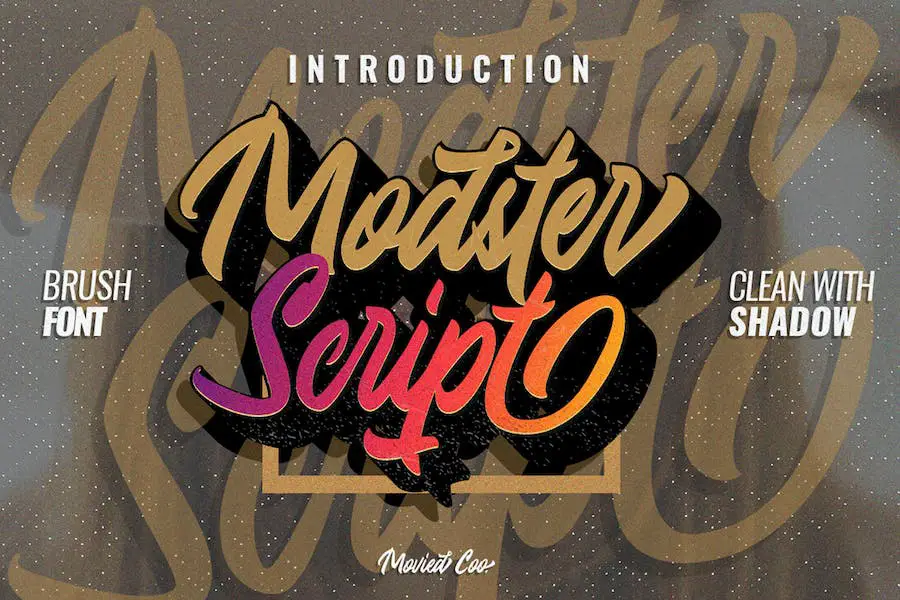
Modster は、プロジェクトのデザインを向上させたいグラフィック デザイナーにとって素晴らしいフォントです。 このシャドウ フォントは、愛情を込めたハンドレタリングからインスピレーションを得た、ユニークで都会的なスタイルを提供します。
さらに、Modster にはさまざまな代替手段が用意されており、デザイナーが実験して独自の個性を加えることができます。 これらの代替案には各文字のオプションが用意されており、デザイナーはこのフォントをカスタマイズして真にユニークなデザインを作成できます。
Modster の際立った機能の 1 つは、追加のシャドウ効果が含まれていることです。 これによりテキストに深みと立体感が加わり、視覚的に魅力的で目を引くものになります。 影を使用すると、全体のデザインが強化され、競合他社よりも目立つようになります。
ブラックロマンス
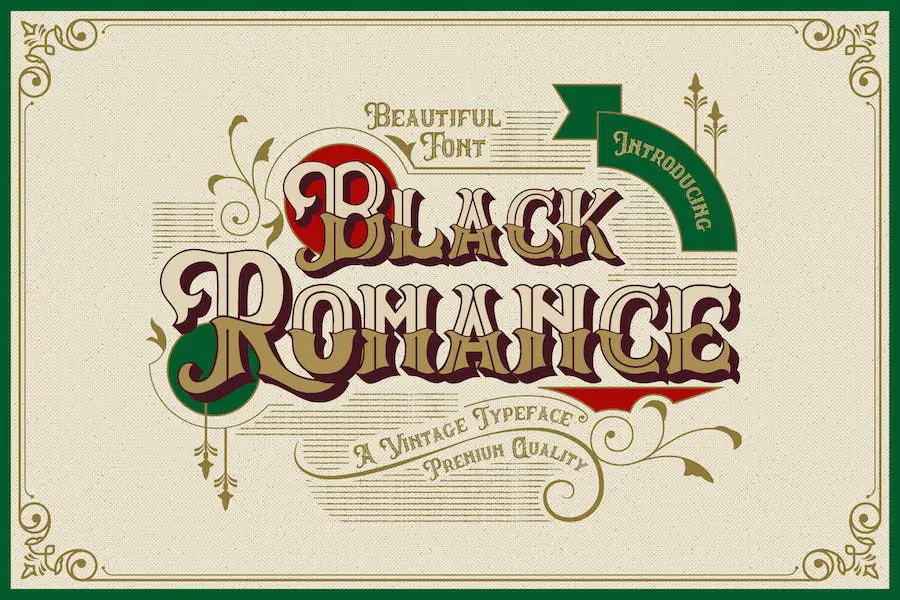
Black Romance は、あらゆるデザイン プロジェクトに優雅さとビンテージ感をもたらす素晴らしいフォントです。 ブラックレターの美しさを備えたこのフォントは、デザインに大胆で装飾的な要素を追加するのに最適です。
このフォントは非常に多用途で、幅広い目的に使用できます。 製品ラベル、ブランディング素材、招待状、バナー、映画タイトルなど、あらゆるものを作成する場合、Black Romance はあなたの作品に魅惑的な魅力を加えます。
ヴィンテージの雰囲気とブラックレターの美学を備えた Black Romance は、デザイン プロジェクトに魅力と洗練さを加えたいと考えている人にとって最適なフォントです。 今すぐダウンロードして、あなたの創造力を羽ばたかせてください。
エルカトラズシャドウ
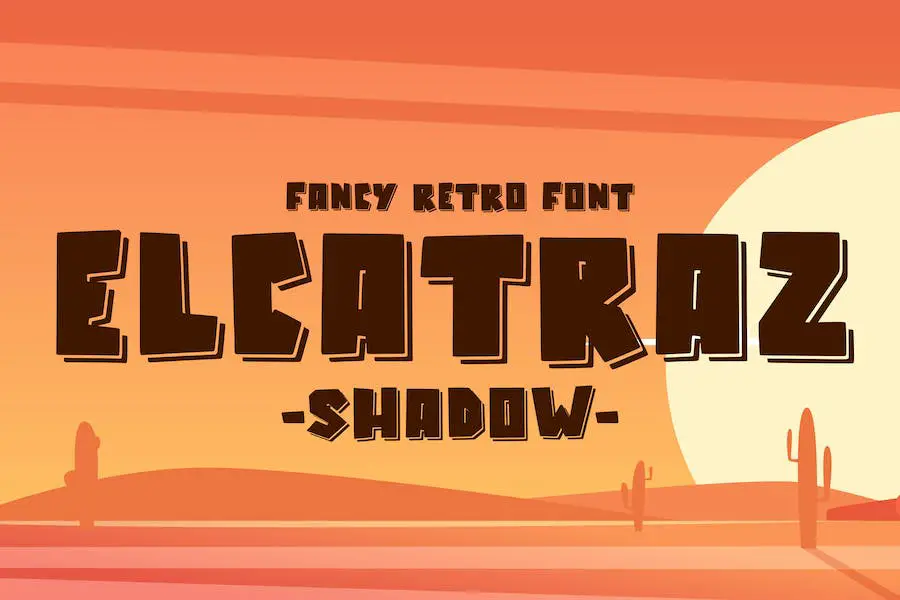
Elcatraz Shadow は、さまざまなクリエイティブ プロジェクトのデザインを強化する多用途フォントです。
工芸品、製品パッケージ、ラベル、ブランディング、ロゴ、ビンテージのソーシャル メディア投稿、広告、透かし、招待状、文具、またはその他のプロジェクトに取り組んでいる場合でも、このフォントは完璧な選択です。
Elcatraz Shadow は、そのユニークなシャドウ効果により、デザインに深みと視覚的な面白みを加え、プロフェッショナルで目を引く外観を与えます。 このフォントをあなたの作品に組み込むと、作品が際立ち、見る人に永続的な印象を残すことになるでしょう。
バーフォード
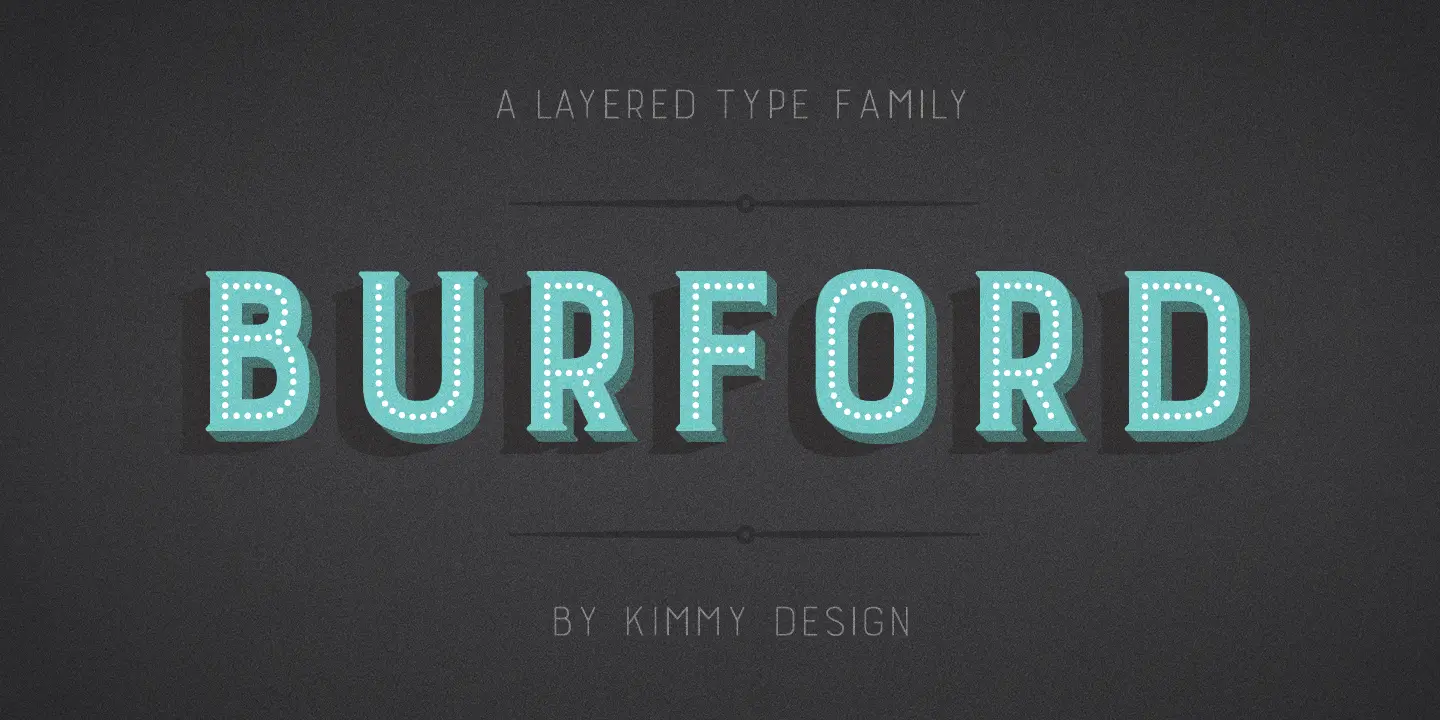
Burford は、Kimmy Design によって作成された注目のシャドウ フォントです。 あらゆるデザインプロジェクトにクールでスタイリッシュなタッチを加え、自分の作品を向上させたいグラフィックデザイナーに最適です。 このフォントには、他のフォントから目立つようにするさまざまな属性が備わっています。
Burford は、その見事なビジュアルに加えて、優れた可読性と可読性も誇っています。 つまり、影の効果があってもテキストは鮮明で読みやすく、メッセージが効果的に伝わります。
したがって、プロジェクトを次のレベルに引き上げるクールなシャドウ フォントを探している場合は、Kimmy Design の Burford 以外に探す必要はありません。 この注目に値するフォントを使用して、デザインにスタイリッシュでプロフェッショナルな雰囲気を与えましょう。
ママキッズ
Moms Kids は、グラフィック デザインの世界における母親と子供のニーズを満たすために設計された、特別なフォントの楽しいセットです。
これらのシャドウ フォントはプロジェクトに独特のタッチを提供し、デザイナーがデザインを向上させ、閲覧者にとって視覚的に魅力的なエクスペリエンスを作成できるようにします。
目立たせるためのさまざまな属性を備えた Moms Kids フォントは、デザインに魅力的で遊び心のある要素を追加したい人にとって必須のフォントです。
あなたのデザインに愛と奇抜なタッチを加えるシャドウ フォントをお探しなら、Moms Kids 以外に探す必要はありません。 これらの特別なフォントは、親愛なる母親と子供たちを念頭に置いてデザインされており、幅広いスタイル、多用途性、細部へのこだわりを備えています。
スーパーリトル
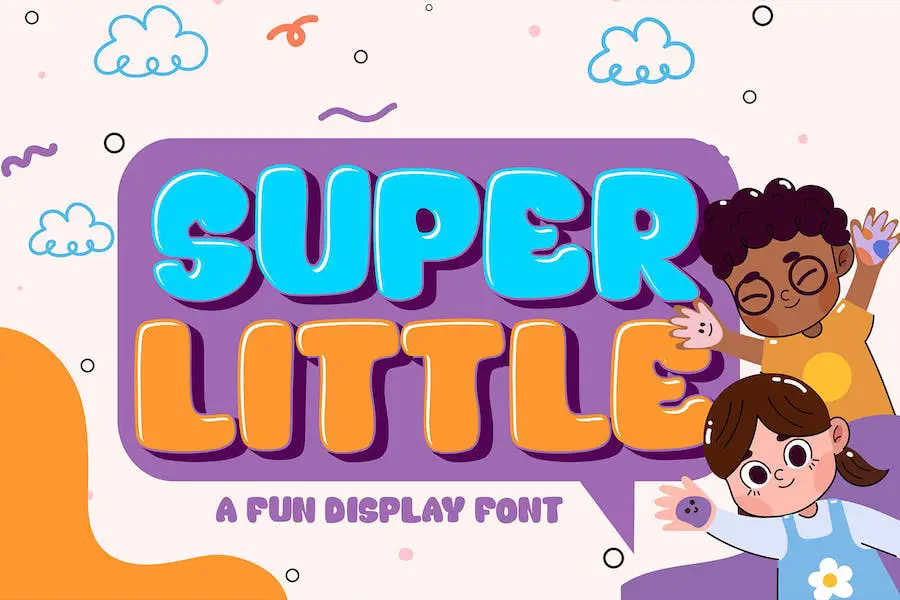
Super Little は、デザイン プロジェクトに影の装飾を加える、楽しくてスタイリッシュな表示フォントです。 ブランディング、見出し、結婚式のデザイン、招待状、またはその他のクリエイティブな取り組みに取り組んでいる場合でも、このフォントはあなたの仕事を次のレベルに引き上げます。
ユニークで人目を引くデザインの Super Little は、ロゴタイプ、ウォールアートのイラスト、ラベルなどの作成に最適です。 この多用途かつダイナミックなフォントでプロジェクトを強化しましょう。
Super Little の優れた点の 1 つは、さまざまなデザイン スタイルに適応できることです。 モダンで洗練された外観を求めている場合でも、ヴィンテージでレトロな雰囲気を求めている場合でも、このフォントはあなたをカバーします。
ビーチデイ
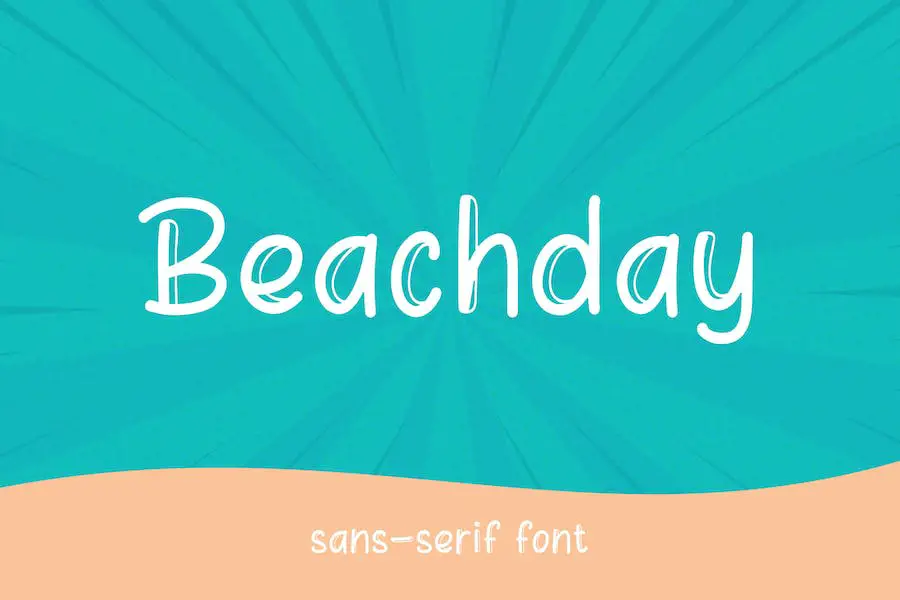
Beachday は、デザインにモダンでクリーンなタッチを加える素晴らしいシャドウ フォントです。 このサンセリフ表示フォントには、すべての単語にハッピーで陽気な雰囲気をもたらす独特の魅力があります。
Beachday の際立った特性の 1 つは、注目を集め、ポジティブな感情を呼び起こす能力です。 フォントのきれいなラインと遊び心のある影の効果が、テキストに喜びと活気をもたらします。
Beachday のもう 1 つの注目すべき特徴は、その読みやすさです。 ユニークでクリエイティブなデザインにもかかわらず、フォントは読みやすく、メッセージが効果的に伝わります。
シャドウビーマー
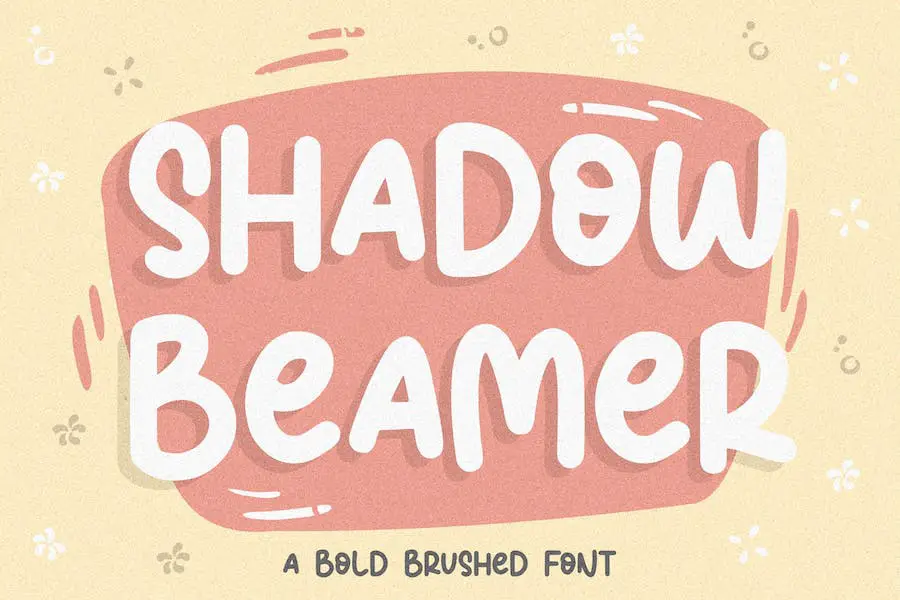
Shadow Beamer は、さまざまなデザイン プロジェクトに最適な、大胆なブラシ フォントです。 製品パッケージの作成、ブランディング プロジェクトの作業、雑誌のレイアウトのデザイン、さらにはソーシャル メディアの投稿のパーソナライズなど、このフォントは優雅さとスタイルのタッチを加えます。
独特のブラシ ストロークが独特の影効果を生み出し、どんな背景に対してもテキストを美しく際立たせます。 Shadow Beamer を使用すると、視覚的に魅力的な方法でメッセージを簡単に表現できます。
素晴らしいシャドウ フォントでプロジェクトを強化したいと考えているグラフィック デザイナーにとっては必需品です。 したがって、Cricut プロジェクトに取り組んでいる場合、Figma でデザインしている場合、または単にデザイン全体を向上させるフォントを探している場合、Shadow Beamer は最適な選択です。
げしな
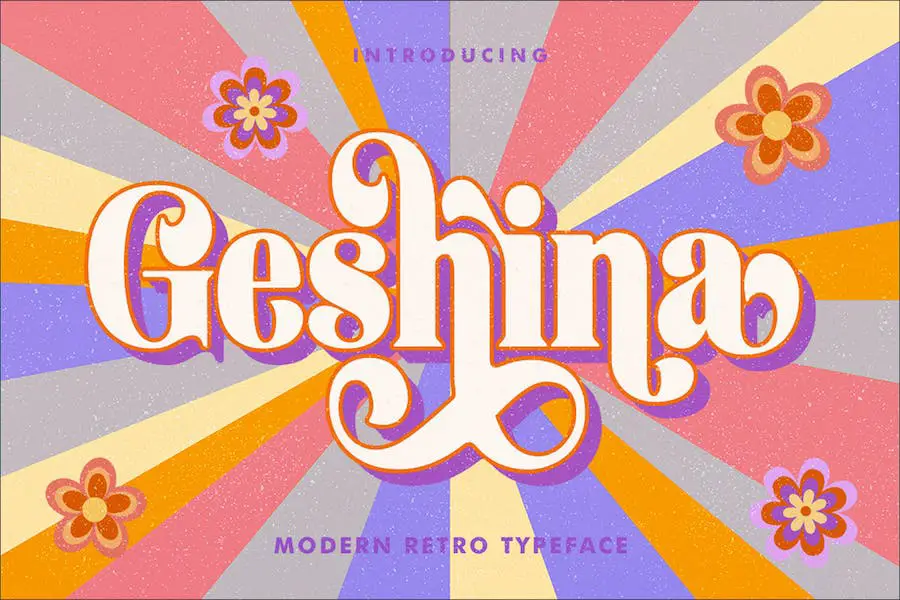
Gesina は、デザインに優雅さを加えるレトロなセリフ フォントです。 曲線的で洗練された文字は、結婚式の招待状、カード、その他ロマンチックで個性的なタッチが必要なデザインの作成に最適です。
Gesina の重要な特性の 1 つは、その多用途性です。 ヴィンテージ風のデザインからモダンでミニマリストなレイアウトまで、このフォントはさまざまなスタイルやテーマにシームレスに適応します。 そのレトロな魅力は、懐かしさを感じさせながらも、新鮮で現代的な感覚を与えます。
Gesina のもう 1 つの大きな特徴は、読みやすさです。 曲線的な文字は目に優しく、本文や長い文章に最適です。 フォントは小さいサイズでも可読性を維持し、メッセージが明確でアクセスしやすいことを保証します。
黒い影
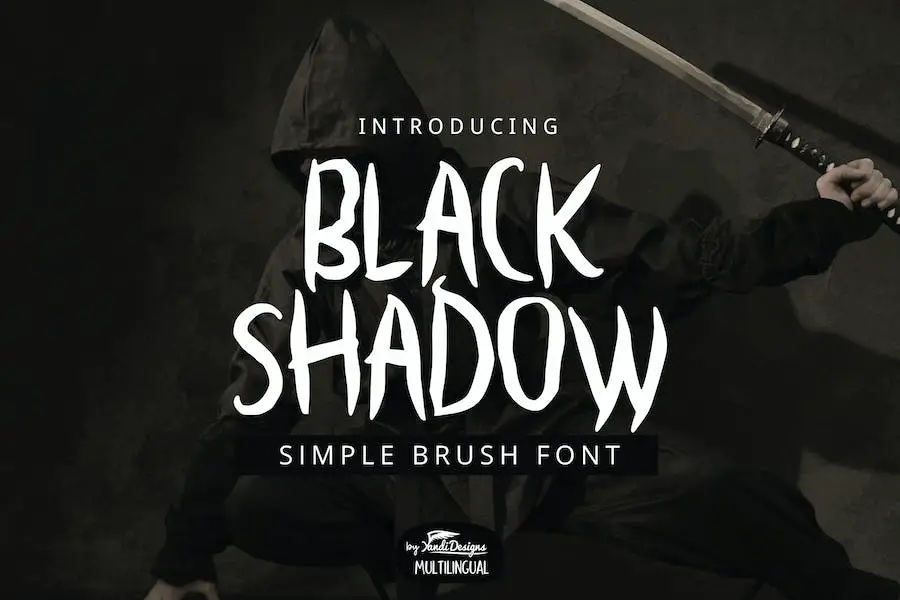
Black Shadow は、あらゆるプロジェクトにシンプルさとユニークさを加える、多用途の手作りブラシ フォントです。 多目的なデザインなので、児童書、引用、ロゴ、見出し、タイトルなどに最適です。
Black Shadow が他のフォントと異なる点は、感情を呼び起こし、雰囲気を作り出す能力です。 手作りのブラシ ストロークはユニークで個人的なタッチを与え、温かみのある心地よい雰囲気を必要とするプロジェクトに最適です。
タトゥー業界にいるなら、Black Shadow は見逃してはいけないフォントです。 その大胆で芸術的なスタイルは、見事なタトゥーのデザインを作成するのに最適です。
ダークサイドシャドウ
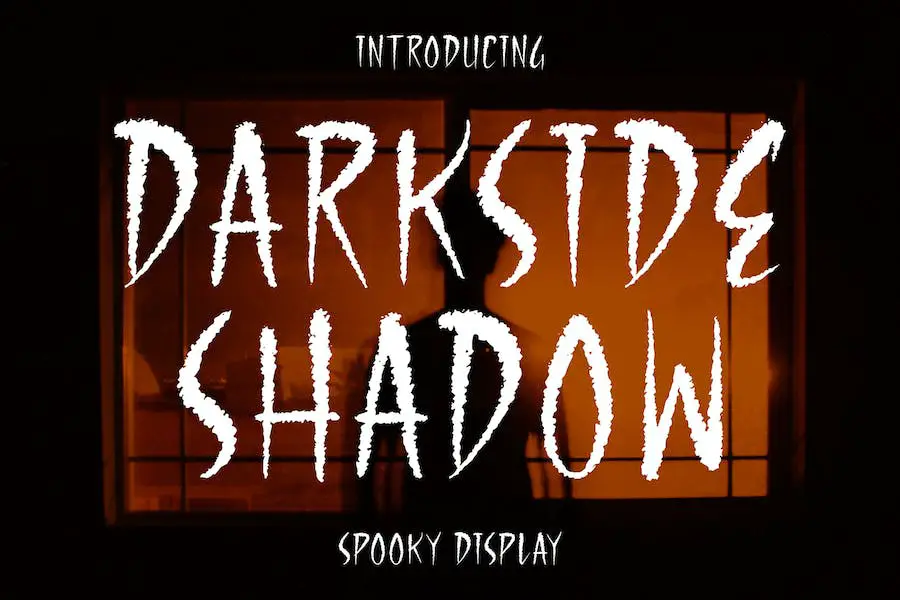
Darkside Shadow は、クリエイティブなプロジェクトに洗練された雰囲気を加える多用途のフォントです。 その洗練されたエレガントなデザインは、ポスター、ソーシャルメディア投稿、ブランド資料などの視覚的魅力を高めるのに最適です。
このフォントは、シームレスで魅力的なユーザー エクスペリエンスを提供するために特別に作成されています。 使いやすさとさまざまなデザイン ソフトウェアとの互換性により、初心者にも経験豊富なグラフィック デザイナーにも便利な選択肢となっています。
Darkside Shadow を使用すると、クライアントに感動を与え、永続的な印象を残す、プロフェッショナルな仕上がりを簡単に実現できます。
影
Shadows は、デザイン プロジェクトに芸術的なセンスをもたらすフォントです。 オリジナルの手書きスタイルを備えたこのフォントは、アパレル、T シャツ、引用符、製品パッケージ、ブランド、ブログ投稿、グリーティング カード、ラベル、ポスター、ウォール アートなどのさまざまな要素を強化するのに最適です。
その多用途性により、どんなデザインにもユニークで目を引くタッチを加えることができます。 あなたがクライアント向けのプロジェクトに取り組んでいるグラフィック デザイナーであっても、単に個人的な作品に磨きをかけたいだけであっても、Shadows はあなたのデザインを次のレベルに引き上げることができます。
大胆で独特な外観を持つこのフォントは、忘れられない印象を残すでしょう。 したがって、デザインに深みと個性をもたらすフォントを探しているなら、Shadows 以外に探す必要はありません。 自己主張を求めるデザイナーにとって必須のアイテムです。
ミッドナイト・シャドウズ
Midnight Shadows は、デザインにキュートでカジュアルな雰囲気をもたらす、驚くほど遊び心のある表示フォントです。 このフォントは、あらゆるプロジェクトに創造性と個性を加えるのに最適です。
独特の影効果により、奥行き感が生まれ、タイポグラフィに視覚的な面白みが加わります。
ロゴ、ポスター、Web サイトのいずれをデザインしている場合でも、Midnight Shadows は魅力的で人目を引く外観を実現するのに役立ちます。 したがって、プロジェクトを次のレベルに引き上げるフォントを探しているグラフィック デザイナーなら、Midnight Shadows 以外に探す必要はありません。
あなたのデザインにちょっとした魔法を加えるのに最適な選択肢です。
黒い影
BLACK & SHADOW は、デザインにモダンなひねりをもたらす、美しい手書きのブラシ フォントです。 衣服、招待状、本、文房具、引用文、ロゴなどの魅力的なタイトルを作成するのに最適です。
小文字、大文字、代替文字、合字、句読点、数字の広範なコレクションを備えたこのフォントは、創造的な表現に無限の可能性をもたらします。
さらに、多言語サポートも提供するため、世界中の視聴者にリーチできます。 BLACK & SHADOW のユニークな魅力と優雅さでデザイン プロジェクトを高めます。
シャドーボクシング
Shadow Boxing は、大胆で重厚なサンセリフと遊び心のある筆文字を組み合わせたユニークなフォント デュオです。 このフォントは、デザインに力強くインパクトのあるタッチを追加するのに最適です。
広告、ロゴ、その他のグラフィック プロジェクトに取り組んでいる場合でも、シャドー ボクシングは永続的な印象を残すことができます。
Shadow-Boxing フォント デュオを使用すると、多用途で信頼できるリソースをすぐに利用できます。 非常に重厚なサンセリフが大胆で威厳のある印象を与え、気楽な筆文字が個性と遊び心を加えています。
この組み合わせにより、フォントを組み合わせてデザインの完璧なバランスを作成することができます。
奇妙な影
プロジェクトにオリジナリティを加えるためにデザインされた、ユニークでクリエイティブなシャドウ フォント「WeirdShadow」を紹介します。 荒々しいエッジと独特のスタイルを備えたこのフォントは、注目を集めて自己主張するのに最適です。
大文字、小文字、数字、記号を備えており、あらゆるデザインのニーズに対応する多用途性を提供します。 タイトル、タイポグラフィー、ポスター、雑誌、パンフレット、パッケージ、ウェブサイトのいずれに取り組んでいる場合でも、「WeirdShadow」はあなたのデザインを向上させ、目立たせることができます。
力強くシャープな美しさがクールな要素を加え、印象に残ります。 あなたのデザインゲームを次のレベルに引き上げるこの素晴らしいフォントをお見逃しなく。
サムライシャドウ
Samurai Shadow は、デザイン プロジェクトを次のレベルに引き上げる素晴らしいフォントです。 このモダンな署名フォントは、美しさ、高級感、優雅さを醸し出しており、幅広いクリエイティブな取り組みに最適です。
Samurai Shadow の素晴らしい点の 1 つは、その多用途性です。 メンズライクにもフェミニンにも使えるデザインなので様々な用途に使えます。
サムライシャドウの優雅さは、あらゆる文字の形に現れています。 きちんとした正確なストロークにより、クリーンで洗練された外観が得られ、わずかな影の効果がテキストに深みと立体感を与えます。 このフォントは本当に目立ち、どんなデザインでも主張します。
プロのグラフィック デザイナーであっても、プロジェクトの視覚的な魅力を高めたいと考えている人であっても、Samurai Shadow は優れた選択肢です。
その多用途性、優雅さ、現代性により、検討する価値のあるフォントです。 サムライ シャドウをあなたのコレクションに加えて、あなたのデザインを新たな高みに引き上げてみてはいかがでしょうか?
怒っている影
Angry Shadow の紹介 – デザイン プロジェクトにゴシックとホラーのスタイルを加えるハロウィーン表示フォントです。
独特の形状と、代替文体、文体セット、合字などのオープンタイプ機能を備えたこのフォントは、目を引くロゴ、ポスター、バッジ、本の表紙、T シャツのデザイン、パッケージなどの作成に最適です。
Angry Shadow は、デザインに不気味で不気味な雰囲気をもたらすように特別に設計されています。 その複雑なディテールと大胆なストロークは、ハロウィーンのテーマの本質を捉えています。 お化け屋敷のチラシでも、不気味なパーティーの招待状でも、このフォントは本当に存在感を発揮します。
代替のスタイルを使用すると、特定のキャラクターをさまざまなバリエーションでカスタマイズするオプションがあり、デザインにさらに多用途性が追加されます。 さまざまな組み合わせを試して、不気味さとスタイリッシュさの完璧なバランスを見つけてください。
最高の無料シャドウフォント
目を引くタイポグラフィーでデザイン プロジェクトを向上させたいと考えていますか? これ以上探さない! この記事セクションでは、作品にさらなる深みとスタイルを確実に加える、最高の無料シャドウ フォントのリストをまとめました。
それでは、早速、見逃せないこれらの素晴らしいオプションを詳しく見ていきましょう。
ディープシャドウ
Imagex の Deep Shadow は、プロジェクトのデザインを強化したいグラフィック デザイナーに最適な、見事なシャドウ フォントです。
このフォントはテキストに深みと立体感を与え、ユニークで目を引く外観を与えます。 複雑な影を備えた Deep Shadow は、あなたのデザインを他よりも際立たせることでしょう。
Deep Shadow の際立った特性の 1 つは、その多用途性です。 ロゴ、ポスター、Web サイトのデザインを作成している場合でも、このフォントはあらゆるプロジェクトに簡単に組み込むことができます。
大胆で表情豊かな文字の形が力強い主張をするとともに、影の効果が視覚的な面白みを加えます。
Deep Shadow のもう 1 つの優れた点は、個人使用であれば無料であることです。 これは、経済的な負担をかけずに、フォントをダウンロードして個人プロジェクトに使用できることを意味します。 予算が限られているものの、プロフェッショナルな仕上がりを実現したいデザイナーにとって、これは素晴らしいオプションです。
影
Vladimir Nikolic の Shadow は、プロジェクトのデザインを強化したいグラフィック デザイナーにとって素晴らしいフォントです。 このフォントは、あらゆるデザインにユニークで目を引く要素をもたらし、他のフォントよりも目立つようにします。
Shadow の属性こそが、Shadow を輝かせるものです。 大胆で印象的な影の効果を持つこのフォントは、テキストに深みと立体感を与え、立体的な外観を与えます。 注目を集める見出しや注目を集めるタイトルを作成するのに最適です。
Shadow の優れた点の 1 つは、個人使用であれば無料であることです。 つまり、ライセンス制限を気にすることなく、独自のプロジェクトで実験できるということです。
これは Vladimir Nikolic からの寛大なオファーであり、デザイナーはこのフォントの創造的な可能性を制限なく活用できます。
光沢のある光沢
Glossy Sheen は、Niscala Huruf によってデザインされた素晴らしいシャドウ フォントです。 洗練されたスタイリッシュな外観を提供し、デザインプロジェクトを大幅に向上させます。 このフォントは、作品に深みと立体感を加えたいグラフィック デザイナーに最適です。
光沢のある光沢を使用すると、テキストに立体感を簡単に与えることができ、テキストを目立たせて視聴者の目を引くようにすることができます。
このフォントによって作成される影は、あらゆるデザインに優雅さと洗練のタッチを追加するため、高級感やプロフェッショナリズムを伝えたいブランドやプロジェクトに最適です。
Glossy Sheen の最も優れた点の 1 つは、個人使用であれば無料であることです。 つまり、このフォントを独自のプロジェクトで無料で試すことができ、制限なく創造性を発揮できるようになります。
ポスター、ロゴ、ソーシャル メディア グラフィックのいずれを作成している場合でも、光沢のある光沢はデザイン ツールキットへの貴重な追加となります。
ホスティル
Hostil は、Intellecta Design によって開発された素晴らしいシャドウ フォントで、プロジェクトのデザインを大幅に向上させることができます。 このユニークなフォントは個人使用であれば完全に無料であり、スタイリッシュで人目を引く書体を必要とするグラフィック デザイナーにとって最高の選択肢となっています。
Hostil は影のある外観で、テキストやデザインに深みと立体感を加えます。 大胆で印象的な文字が力強い主張をし、作品に注目を集めます。
ロゴ、ポスター、デジタル グラフィックのいずれを作成している場合でも、このフォントはデザインにプロフェッショナルで洗練された外観を与えます。
Hostil の特性により、視覚的に強いインパクトを必要とするプロジェクトに最適です。 すっきりとした読みやすいデザインにより、小さなサイズでもテキストが読みやすくなります。
シャドウ効果により、洗練されたスタイルがさらに追加され、デザインが群を抜いて目立ちます。
ジャイアンツ
Billy Argel Fonts の GIANTS は、プロジェクトのデザインを大幅に強化できるシャドウ フォントの素晴らしいコレクションです。
これらのユニークで人目を引くフォントは、テキストに深みと立体感を与え、大胆でドラマチックな外観を与えます。 GIANTS を使用すると、魅力的な見出し、ロゴ、ポスターなどを簡単に作成できます。
GIANTS コレクションの各フォントは、創造性と細部へのこだわりで知られる才能あるフォント デザイナーである Billy Argel によって慎重に作成されています。 フォントは個人使用であれば無料なので、あらゆるレベルのデザイナーがアクセスできます。
プロのグラフィック デザイナーであっても、個人的なプロジェクトに磨きをかけたいと考えている人であっても、これらのフォントは素晴らしい選択肢です。
ジャイアンツの特徴の一つは、その多彩なスタイルです。 エレガントで洗練されたものからエッジの効いたモダンなものまで、それぞれのフォントには独自の個性があります。 この多様性により、プロジェクトのトーンやテーマに一致する完璧なフォントを見つけることができます。
オレタンズ
InksTypia Studio の Oretans をご紹介します。これは、デザイン プロジェクトを新たな高みに引き上げる素晴らしいシャドウ フォントのコレクションです。 これらのフォントは、作品に深みと次元を加えるスタイリッシュでユニークな方法を探しているグラフィック デザイナーに最適です。
Oretans を使用すると、印象に残る目を引くデザインを簡単に作成できます。
これらのシャドウ フォントには幅広いオプションがあり、プロジェクトに最適なスタイルを選択できます。 大胆でドラマチックなものからエレガントで洗練されたものまで、このコレクションにはあらゆる美学に合うフォントが含まれています。
独特の影効果を備えたこれらのフォントは、あらゆるデザインに創造性とプロフェッショナリズムを加えます。
Oretans の素晴らしい点の 1 つは、個人使用の場合は無料であるため、予算に余裕のあるデザイナーにとって手頃な選択肢となることです。 個人的なプロジェクトに取り組んでいる場合でも、クライアントのデザインに取り組んでいる場合でも、大金を掛けずにこれらのフォントを使用できます。
このアクセシビリティにより、追加費用を心配することなく Oretans のメリットを享受できるようになります。
コミカ
Komyca は、グラフィック デザイン プロジェクトの視覚的な魅力を高めるために設計された最上級のシャドウ フォントです。 Alit Design によって作成されたこのフォントは、デザインを強化し、視聴者を魅了する一連の魅力的な属性を誇っています。
洗練されたモダンなスタイルを備えた Komyca は、テキスト、ロゴ、見出しなどに奥行きと立体感を加えるのに最適です。 印刷物、Web サイト、ソーシャル メディア グラフィックのいずれで作業している場合でも、このフォントは印象的な印象を与えるでしょう。
何よりも、個人使用の場合は無料なので、あらゆるレベルのデザイナーにとってアクセスしやすく、手頃な価格のオプションになります。 退屈で平坦なタイポグラフィーに別れを告げ、Komyca のスタイリッシュで洗練されたものをクリエイティブな取り組みに歓迎します。
ハイアップ
HIGHUP は、Billy Argel Fonts によってデザインされた無料のシャドウ フォントで、プロジェクトのデザインを強化したいグラフィック デザイナーに最適です。 ユニークなスタイルと注目を集める影を備えたこのフォントは、あなたのデザインを際立たせることでしょう。
HIGHUP フォントの特徴には、あらゆるテキストに奥行きと立体感を加える、洗練されたスタイリッシュなデザインが含まれます。 このフォントの影は視覚的に魅力的な効果を生み出し、デザインにプロフェッショナルで洗練された外観を与えます。
ロゴ、ポスター、Web デザインのいずれに取り組んでいる場合でも、HIGHUP はプロジェクトを新たな高みに引き上げます。
HIGHUP の無料個人使用ライセンスにより、デザイナーは制限なくこのフォントを実験して個人プロジェクトに組み込むことができます。 Billy Argel Fonts は、デザイナーにデザインを強化するために使用できるクリエイティブなツールを提供することを目的としてこのフォントを作成しました。
ローズ・サリー
Rose Sally は、あらゆるデザイン プロジェクトに楽しさをもたらす、楽しくて遊び心のある書体です。 魅力的で子供をテーマにしたスタイルは、子供関連のプロジェクトやかわいい引用文のための人目を引くデザインの作成に最適です。
ユニークで風変わりな雰囲気を持つこのフォントは、遊び心のある要素を追加し、デザインに喜びの感覚をもたらすことができます。 何よりも、個人使用の場合は無料なので、制限なくプロジェクトに簡単に組み込むことができます。
したがって、自分のデザインに魅力と奇抜さを加えたい場合は、Rose Sally が最適です。 ぜひ試してみて、あなたの創造力を発揮してください!
よくある質問
シャドウ フォントは、影や立体感があるように見えるタイポグラフィの一種です。 テキストに深みと立体感を加え、視覚的に面白く、目を引くものにします。
シャドウ フォントは、テキストの視覚的な魅力を高める優れた方法です。 デザインを際立たせ、ユニークでスタイリッシュな外観を与えることができます。 シャドウ フォントは、ロゴのデザイン、見出し、タイトルに奥行きとインパクトを与えるためによく使用されます。
結論
結論として、グラフィック デザイン プロジェクトを確実に強化する 27 個の最高のシャドウ フォントを検討しました。 クラシックでエレガントなオプションから、より大胆でモダンなオプションまで、あらゆるスタイルや目的に合ったフォントがあります。
印刷メディア用にデザインしている場合でも、デジタル メディア用にデザインしている場合でも、これらのフォントはデザインに深みと立体感を加えます。